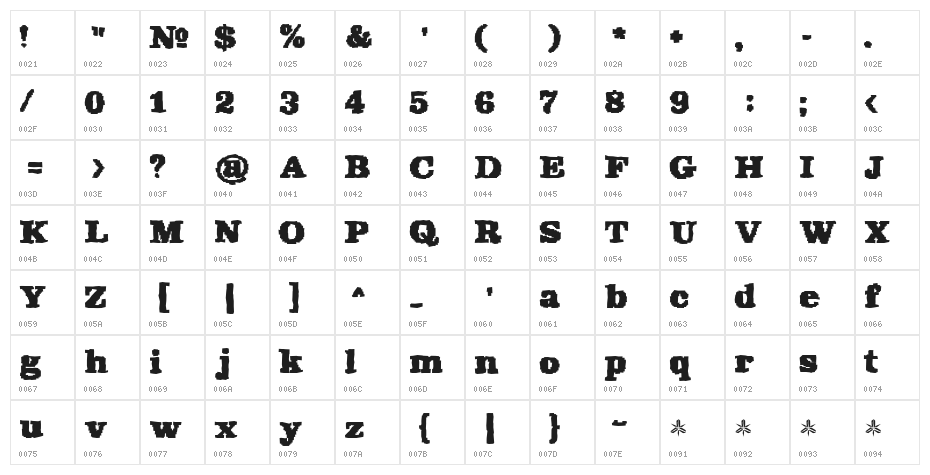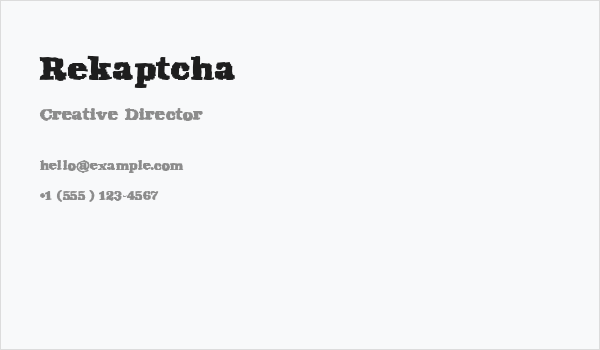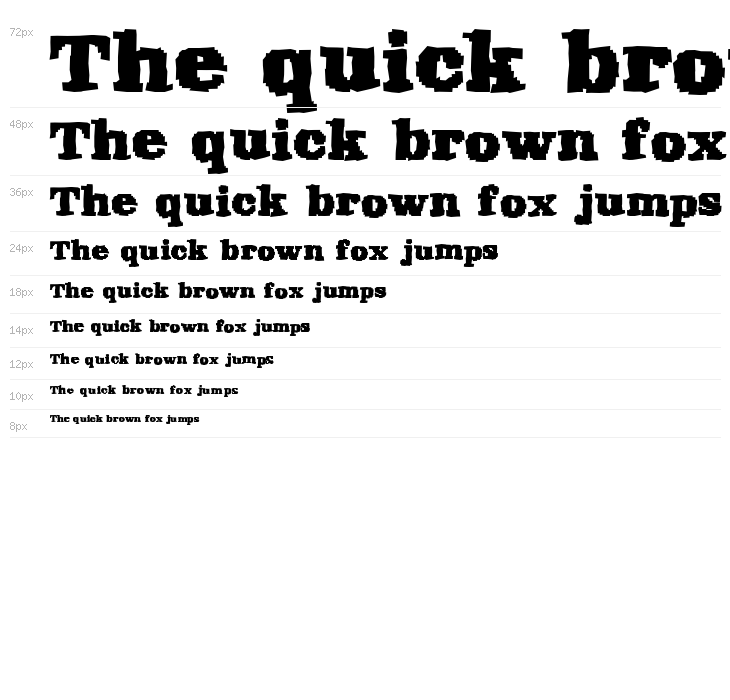
Rekaptcha Font
✎ Distorted Eroded
| Stile generale | Vintage, Industrial, Grunge |
| Progetti proposti | Ideal for posters, album covers, branding for edgy or industrial-themed products, and any design needing a bold, vintage touch. |